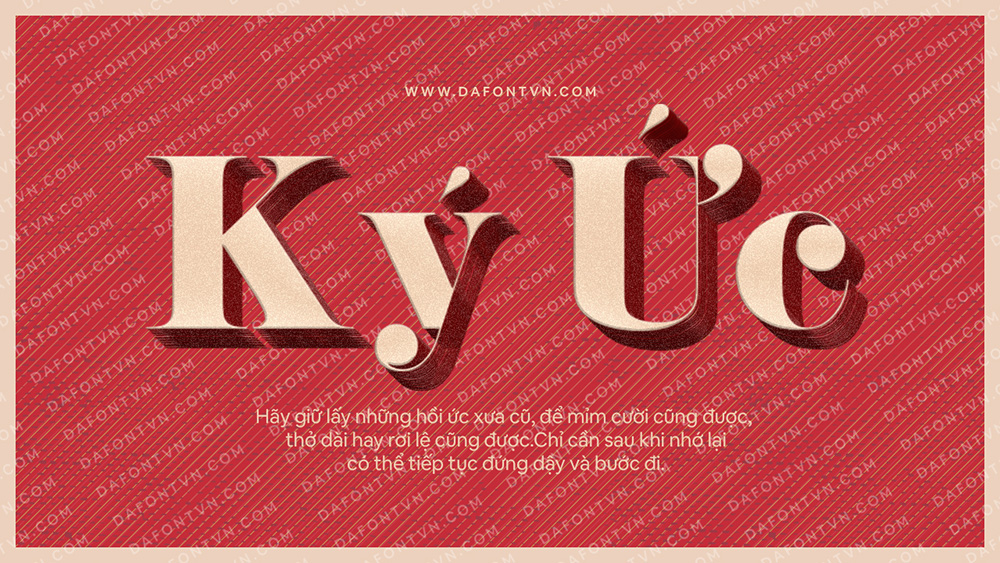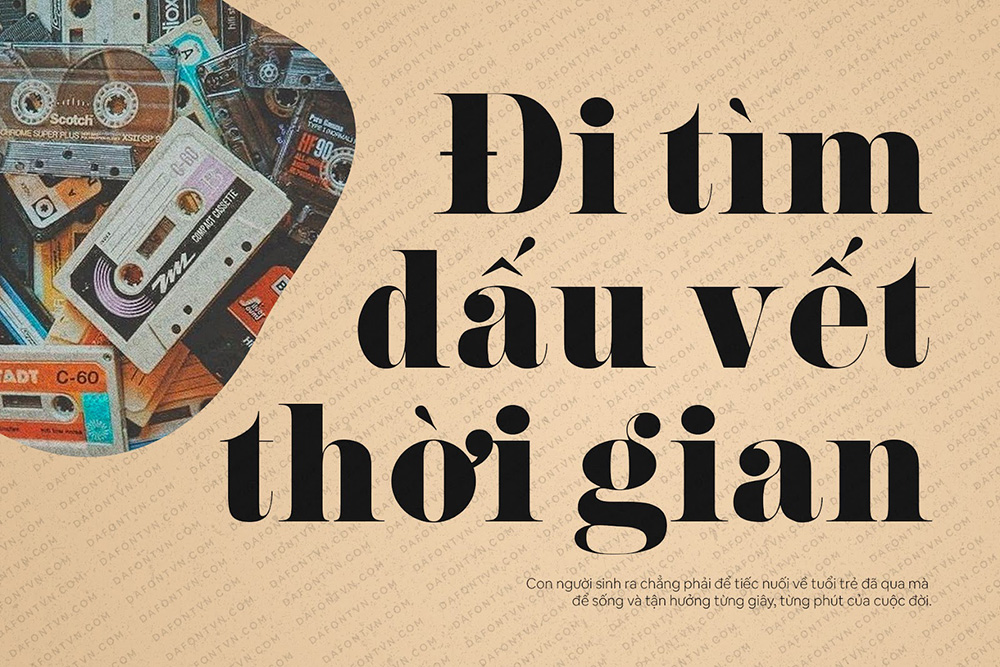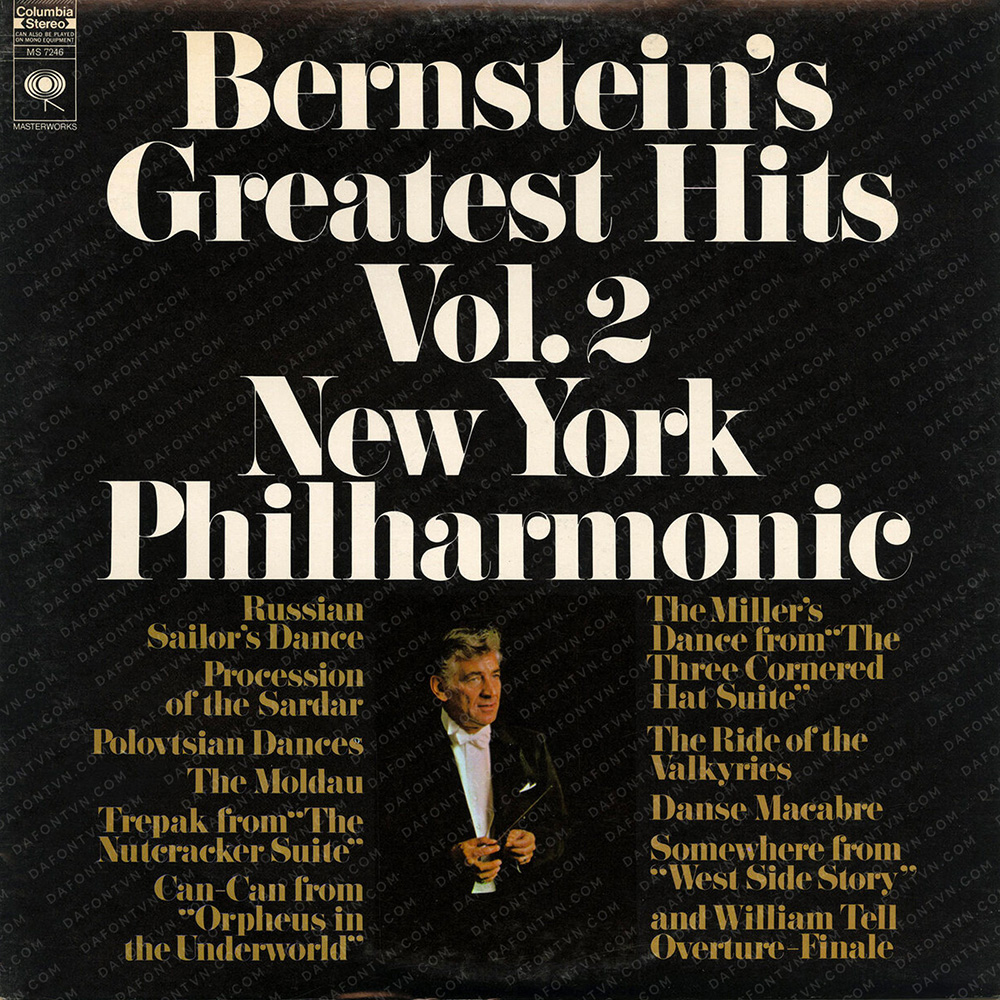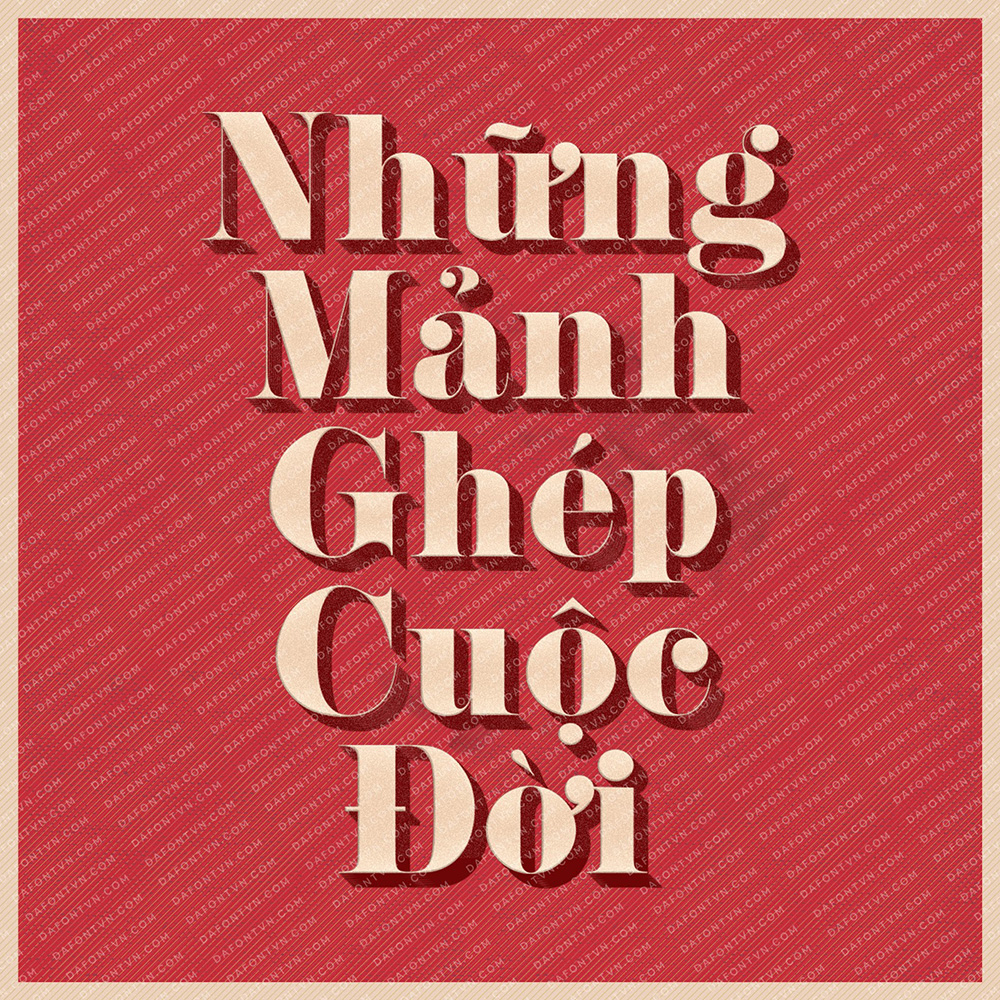
Font Việt Hóa - Pistilli Roman Mang Phong Cách Cổ Điển
Pistilli Roman là một kiểu chữ photocompositor được thiết kế hợp tác bởi Herb Lubalin và John Pistilli. Nó được phát hành lần đầu tiên vào năm 1964.
Với công nghệ của thời điểm Pistilli Roman được sản xuất, kiểu chữ này chỉ được thiết kế và tạo ra chức năng để sử dụng trên máy đánh máy, kiểu chữ này chưa bao giờ chính thức được sử dụng, được số hóa. Bởi vì Pistilli Roman là một kiểu chữ độc quyền đã được chào đón nhờ các ký hiệu rất thanh lịch và độc đáo của nó, nhiều kiểu chữ trông giống nhau bắt đầu xuất hiện.
Vào năm 1969, Phil Martin đã tạo ra một bản sao Pistilli Roman với nhiều dấu gạch ngang giống nhau và các ký tự thay thế có tên là Didoni. Sự khác biệt là Didoni có các nét chân thường dày hơn và cũng thiếu các ký hiệu lạ mắt vốn là nhãn hiệu của Pistilli Roman.
Việc số hóa không chính thức lần đầu tiên của Pistilli Roman được cho là đã được thử nghiệm bởi một xưởng đúc chữ Castcraft và thời kỳ đầu những năm 1990.